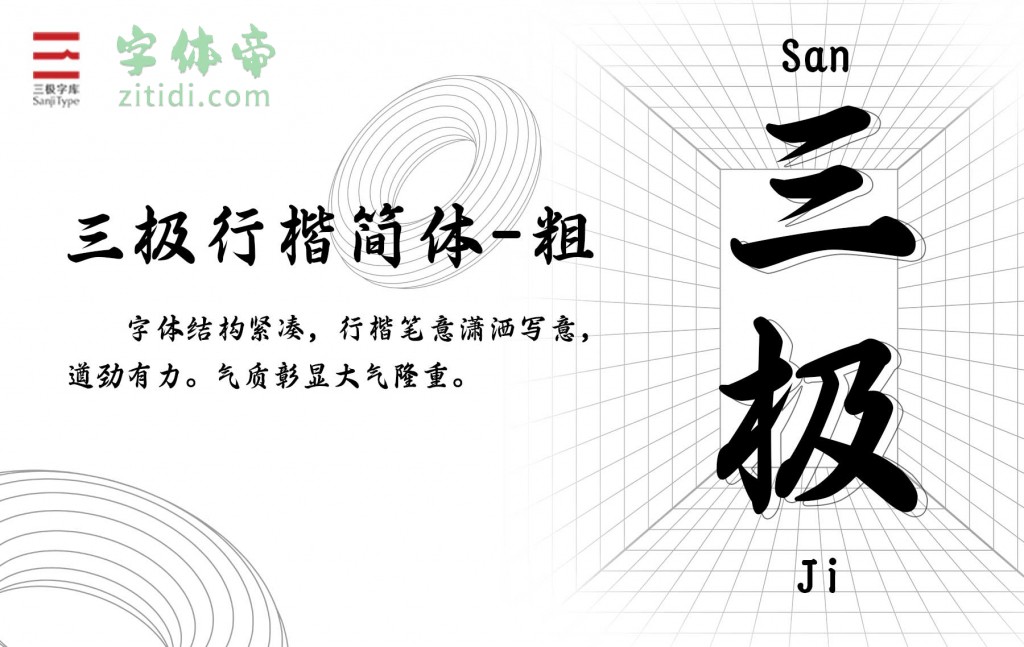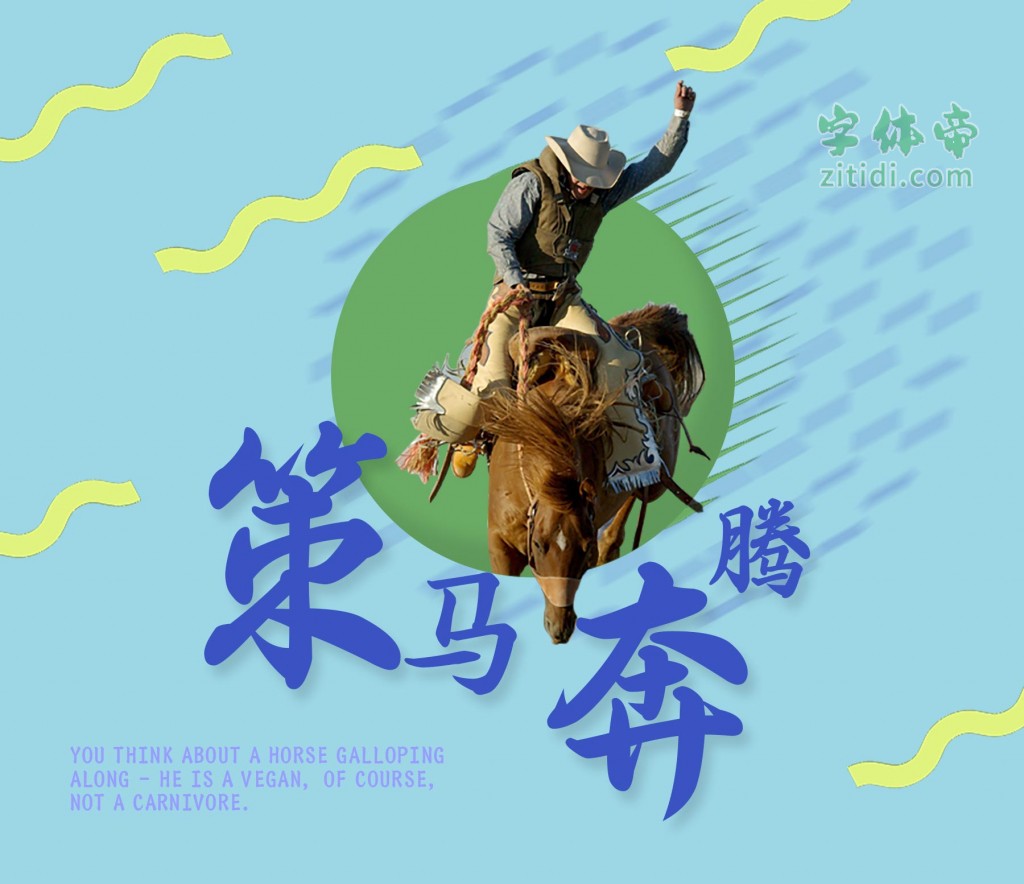
三极行楷简体-粗字体信息
三极行楷简体字体结构紧凑,行楷笔意潇洒写意,遒劲有力。以春联为名,气质彰显大气隆重。本作品适用于印刷媒介的标题及广告语、各类屏幕显示及影视字幕、游戏等。
适用媒介:杂志、书籍、广告、标志、宣传册、店招、包装、影视、动漫、游戏。
“三极行楷简体-粗”是一款书写很新颖的字体,字体大方,适合各种设计作品使用!欢迎下载!